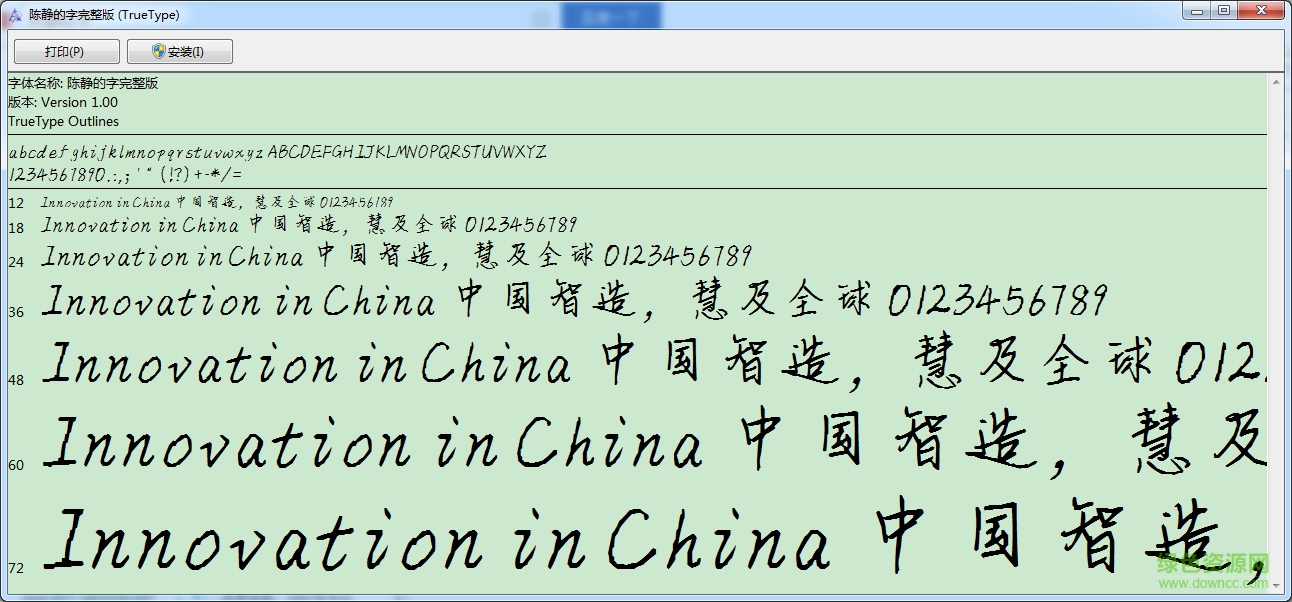
陳靜的字完整版是一款非常漂亮的簡(jiǎn)體字體,這款字體細(xì)化纖細(xì),字形優(yōu)美,整體效果非常出色,喜歡這款字體的朋友歡迎來(lái)綠色資源網(wǎng)下載使用!
陳靜的字完整版,它是北大計(jì)算機(jī)科學(xué)技術(shù)研究所研發(fā)的中文字庫(kù)自動(dòng)生成系統(tǒng)生成的字體,作者北大陳靜。該字體有點(diǎn)類(lèi)似于卡通效果,整體風(fēng)格非常出色,字庫(kù)完整,可以適用于名片設(shè)計(jì)、平面設(shè)計(jì)、廣告設(shè)計(jì)、報(bào)紙雜志等領(lǐng)域